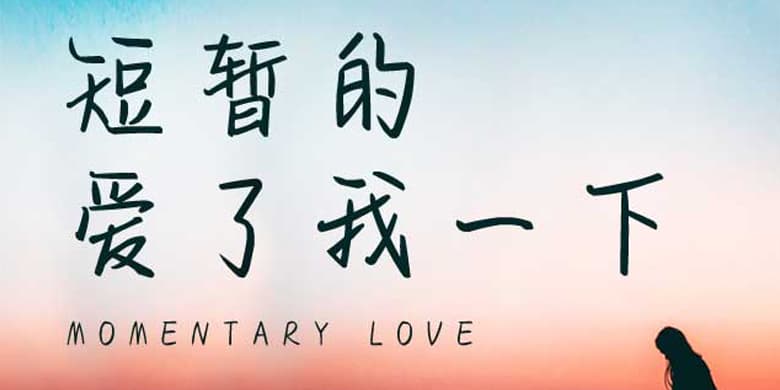
品牌:方正手迹设计师:王航发行时间:2020字库编码:简繁扩展(GBK)分类:常规书写·硬笔字体属性:精品字
短暂的爱了我一下这款字体用笔考究,起收笔触表现明显,字形上松下紧,韵味十足。适用于文艺类的书刊、品牌广告和产品包装设计,以及社交网络的个性化用字。
品牌:方正手迹设计师:王航发行时间:2020字库编码:简繁扩展(GBK)分类:常规书写·硬笔字体属性:精品字
短暂的爱了我一下这款字体用笔考究,起收笔触表现明显,字形上松下紧,韵味十足。适用于文艺类的书刊、品牌广告和产品包装设计,以及社交网络的个性化用字。